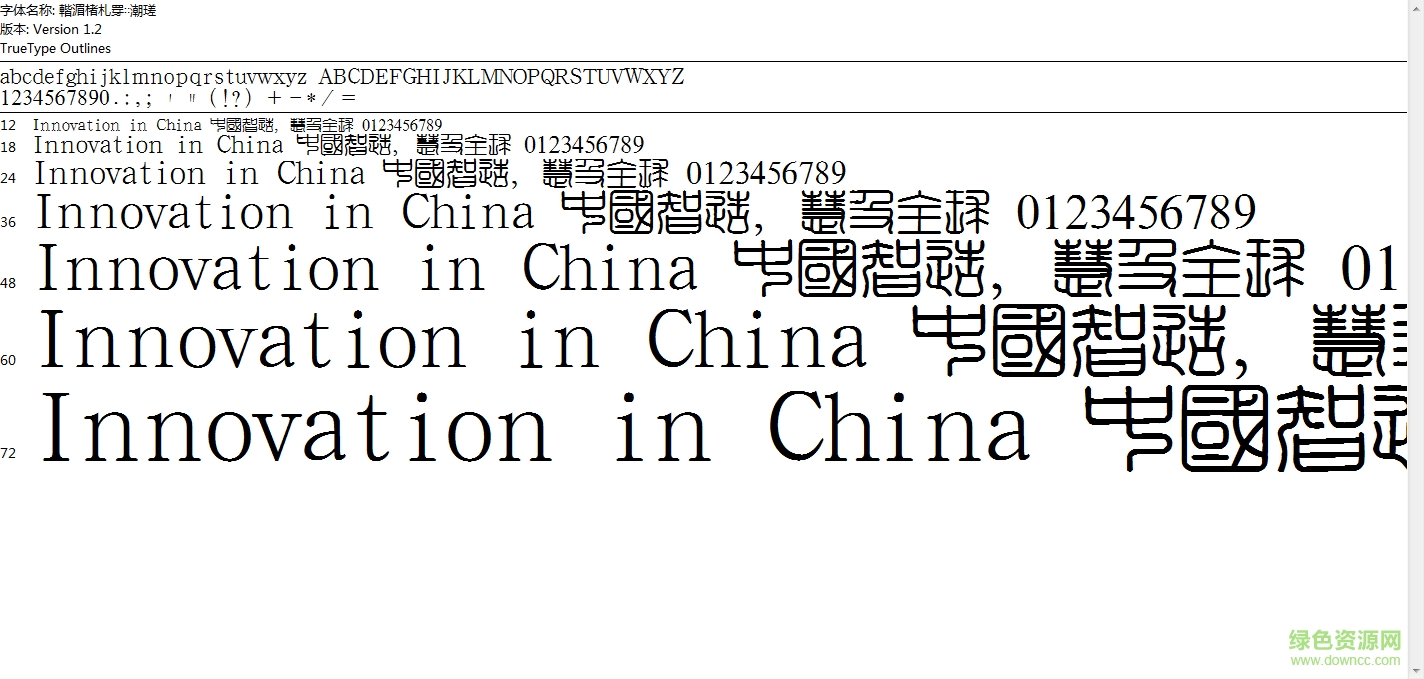
漢鼎繁特圓字體是小編比較喜歡的一種字體。使用它輸出的字體外觀上比較平整,用來(lái)設(shè)計(jì)一些大標(biāo)題的話非常合適。在印刷、平面設(shè)計(jì)方便使用的較為廣泛!
漢鼎繁特圓是一款簡(jiǎn)潔美觀的字體,此款字體字型圓潤(rùn)、粗細(xì)均勻,整體效果非常出眾,廣泛應(yīng)用于廣告設(shè)計(jì)、包裝印刷、平面設(shè)計(jì)等領(lǐng)域,歡迎來(lái)綠色資源網(wǎng)下載!